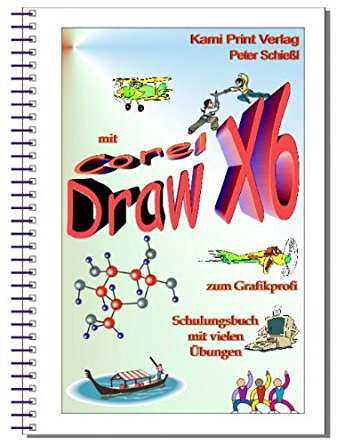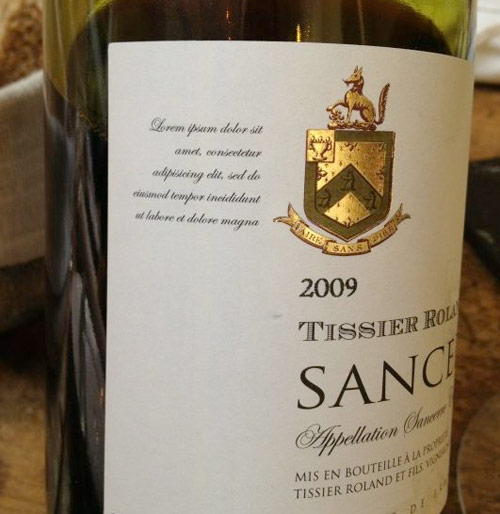
Jetzt muss ich doch auch mal ein Meisterstüch der Gestaltungskunst präsentieren, ein Meisterwerk der Buchgestaltung für ein Lehrbuch, das einem zum Grafikprofi macht. Klasse gelngen! :hammer::party: Besonders schon die geniale Font-Auswahl : :huhu::peng:
Ja, das sollte ich mir dringend kaufen! Wie man so etwas mit Schrift machen kann, habe ich nämlich bis heute nicht begriffen.  ;-)
Der Autor handelt schließlich mit Brauereitechnik. Von dem kannst Du bestimmt in Sachen Graphik noch was lernen.
Wieso, macht doch war her, so ein lateinischer Sinnspruch neben dem güldenen Wappen und dann noch die Escorial. :party:
Da es die Etiketten bis auf die Flasche geschafft haben, hat es der Kunde ja offensichtlich nicht mal bemerkt.
Eben. Das sieht für den Laien nach altem Wein aus gutem Hause aus. Vielleicht war Lorem ipsum ja richtig verkaufsfördernd und niemand hat in die Tischkante gebissen, sondern stattdessen mit einem Glas Roland Tissier & Fils auf die eigene Genialität angestoßen.
Hat eigentlich jemand ein Copyright für "lorem ipsum" oder erwirbt ein Kreativmensch ein solches, wenn er diesen Text markant einsetzt?
Hat eigentlich jemand ein Copyright für "lorem ipsum" …
Da habe ich vorhin auch schon (ergebnislos) drüber nachgedacht.
Ich glaube, das Lorem Ipsum von jemand in Sidi Ahmet (Marocco) erfunden wurde, um Mediengestalter in die Panik zu treiben. Etwas verschlüsselt steht ja die Qelle ja drin :-)
Nem ist natürlich blödsinn, Lorem Ipsum ist Public Domain.
Die deutsche Wikipedia sagt
Als Platzhaltertext sollen Lorem-ipsum-Passagen seit dem 16. Jahrhundert bei Setzern üblich gewesen sein. Seit den 1960er Jahren verwendet die Firma Letraset sie zur Demonstration der Gestalt verschiedener Schrifttypen. Auch sonst finden sich viele leicht voneinander abweichende Varianten dieses Textes.
Wenn es tatsächlich seine Wurzeln im 16. Jh. hat, ist ein mögliches Urheberrecht ja eh verfallen. Aber wenn wir hier einen findigen Anwalt im Forum hätten, könnte man vielleicht trotzdem reich damit werden, allen anderen eine Unterlassung zu Verordnen ;-)
Ich kann mich nicht erinnern, jemals im Bleisatz einen Platzhaltertext verwendet oder auch nur gesehen zu haben. Im Bleisatz hat man vorher viel mehr abstrahiert und berechnet als gezeigt, die Herstellung eines Platzhaltertextes wäre ja auch verhältnismäßig teuer gewesen. Copy and Paste geht mit Blei nun mal nicht.
Platzhalter im Bleisatz, nannte man sowas nicht Blindmaterial? :party:
Flächen, die für irgendetwas reserviert waren, was noch nicht da war, wurden mit Blindmaterial blankgeschlagen.
Manchmal rutschen nicht nur Platzhalter-Texte durch, sondern wohl auch Platzhalter-Bilder. Oder es war ganz anders: Gestalter: Also das hier ist nur ein Platzhalter, da muß der Photograph dann noch … Kunde: Ach nö, das ist doch schön, das lassen wir so …